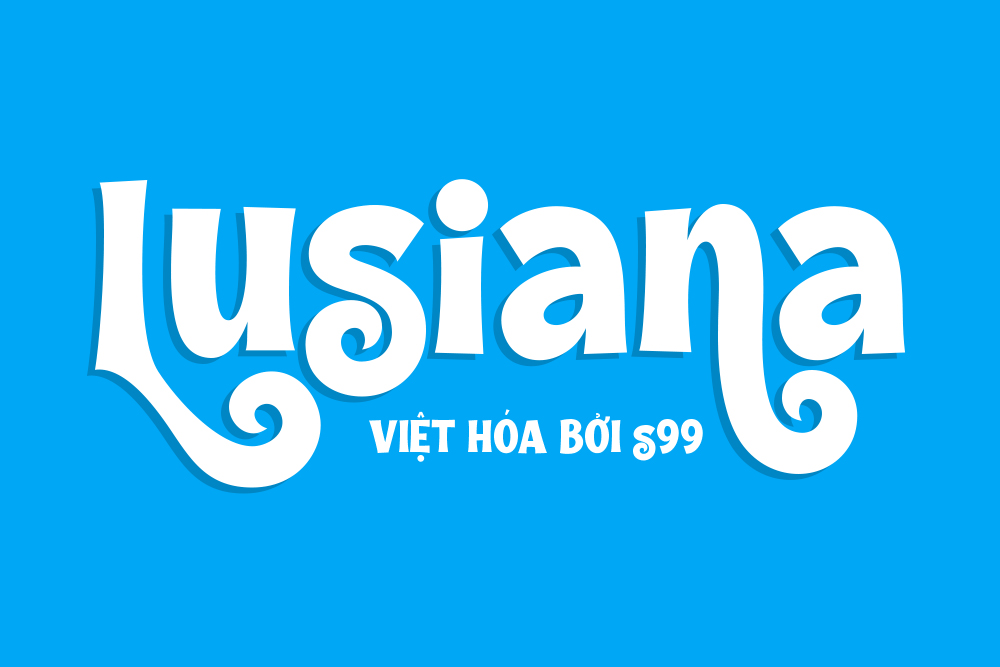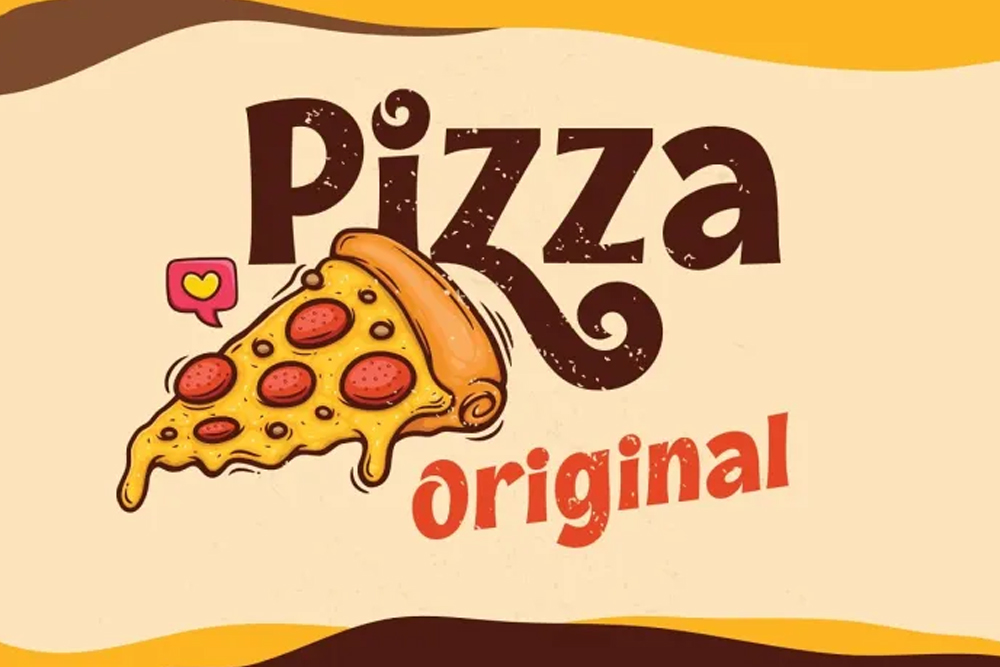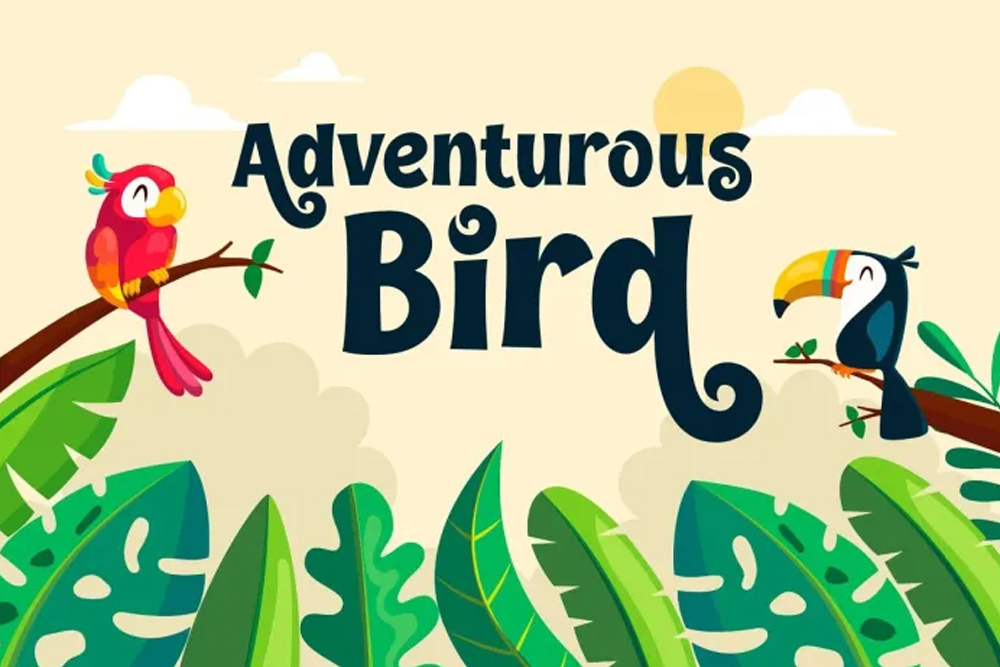
Font chữ hoạt hình TH Lusiana Việt Hóa
Tác giả Toni Dzulham
Bạn đang tìm kiếm một font chữ hoạt hình đáng yêu, mềm mại và đậm chất cá nhân cho các thiết kế sáng tạo của mình? TH Lusiana chính là một trong những lựa chọn tuyệt vời cho năm 2025 – mang phong cách viết tay tươi vui, thân thiện, đặc biệt phù hợp với các sản phẩm dành cho trẻ em, thiệp mời, sticker, sách tô màu hoặc video hoạt hình.
Font chữ hoạt hình TH Lusiana là gì?
TH Lusiana là một kiểu font chữ hoạt hình viết tay được thiết kế bởi DumadiStyle (Gian Studio), với phong cách tự nhiên, vui tươi và gần gũi. Các nét chữ tròn trịa, uốn lượn mềm mại tạo nên cảm giác như được vẽ bằng tay – rất giống với các font thường thấy trong phim hoạt hình, truyện tranh, poster thiếu nhi.
Không chỉ dễ thương, TH Lusiana còn đã được Việt hóa đầy đủ, hỗ trợ hoàn chỉnh dấu tiếng Việt, giúp bạn dễ dàng sử dụng trong các thiết kế cần yếu tố ngôn ngữ tiếng Việt như menu quán trẻ em, tiêu đề website, áp phích dạy học…
Vì sao TH Lusiana là font chữ hoạt hình lý tưởng?
Viết tay mềm mại – tạo hình sinh động
Nét chữ của TH Lusiana mang lại sự sống động, như thể bạn đang đọc lời thoại trong một cuốn truyện hoạt hình. Nhẹ nhàng, dễ đọc, không cầu kỳ nhưng vẫn có cá tính riêng biệt.
Phong cách tươi sáng, thân thiện
Phù hợp với thiết kế giáo dục, sản phẩm trẻ em, app học tập, bìa sách thiếu nhi, video hoạt hình, sticker...
Việt hóa đầy đủ
Phiên bản Việt hóa bởi Phạm Sơn - Admin Fontdep và S99.VN giúp bạn dùng được mọi dấu tiếng Việt – từ “ă”, “â”, “ê” đến “đ”, mà không bị lỗi font hay sai định dạng.
Kết luận: Font Lusiana – lựa chọn lý tưởng cho thiết kế hoạt hình
Nếu bạn đang tìm kiếm một font chữ hoạt hình Việt hóa có nét viết tay ngộ nghĩnh, thân thiện, dễ đọc và dễ ứng dụng, thì TH Lusiana là gợi ý cực kỳ phù hợp. Từ poster thiếu nhi, sách truyện, đến video YouTube hoặc app học tập – font này sẽ giúp bạn thể hiện trọn vẹn cá tính dễ thương và sự gần gũi trong từng thiết kế.